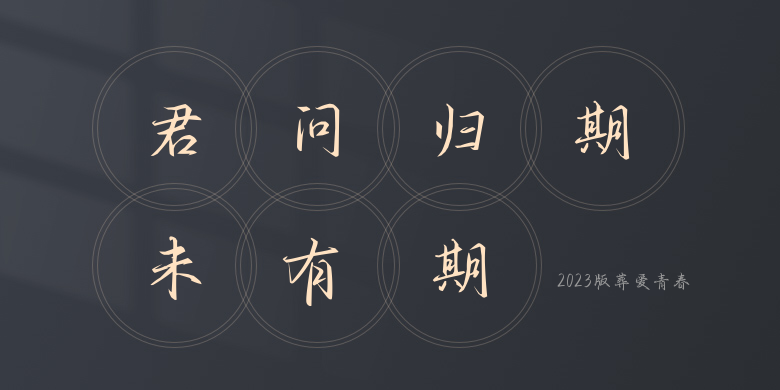
2023版葬爱青春
2023版葬爱青春,这款字体结构工整、笔画清晰,兼顾美观与易读性,适用于标题、正文、海报、包装、LOGO 等多种场景。字形优雅稳定,风格百搭耐看,适配日常排版与创意设计,让文字呈现更舒适、更具质感。2023版葬爱青春一笔一画,皆是细节,以均衡的比例、流畅的线条打造舒适视觉体验,字形端正大气,风格简约现代。无论是商业设计、品牌宣传还是日常排版,都能轻松驾驭,让文字更有格调与力量。2023版葬爱青春字体下载。